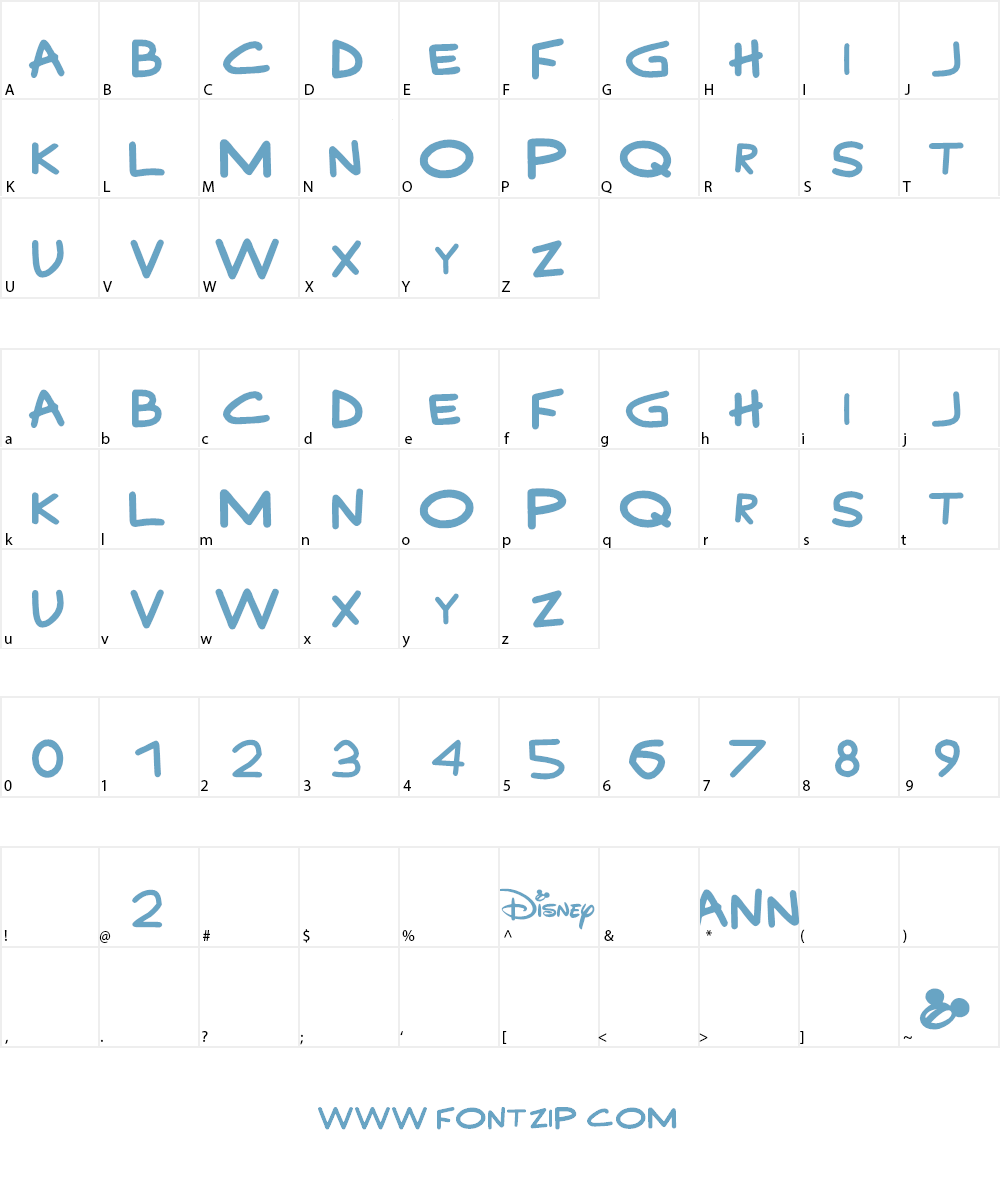
Registro de cambios para la versión 2.0 (10/10/2017):
* Se agregaron números, ~ (Punto con orejas de ratón), ^ (Logotipo de Disney)
Registro de cambios para la versión 1.0 (2/6/2017):
* Se creó la fuente
* Se agregaron letras